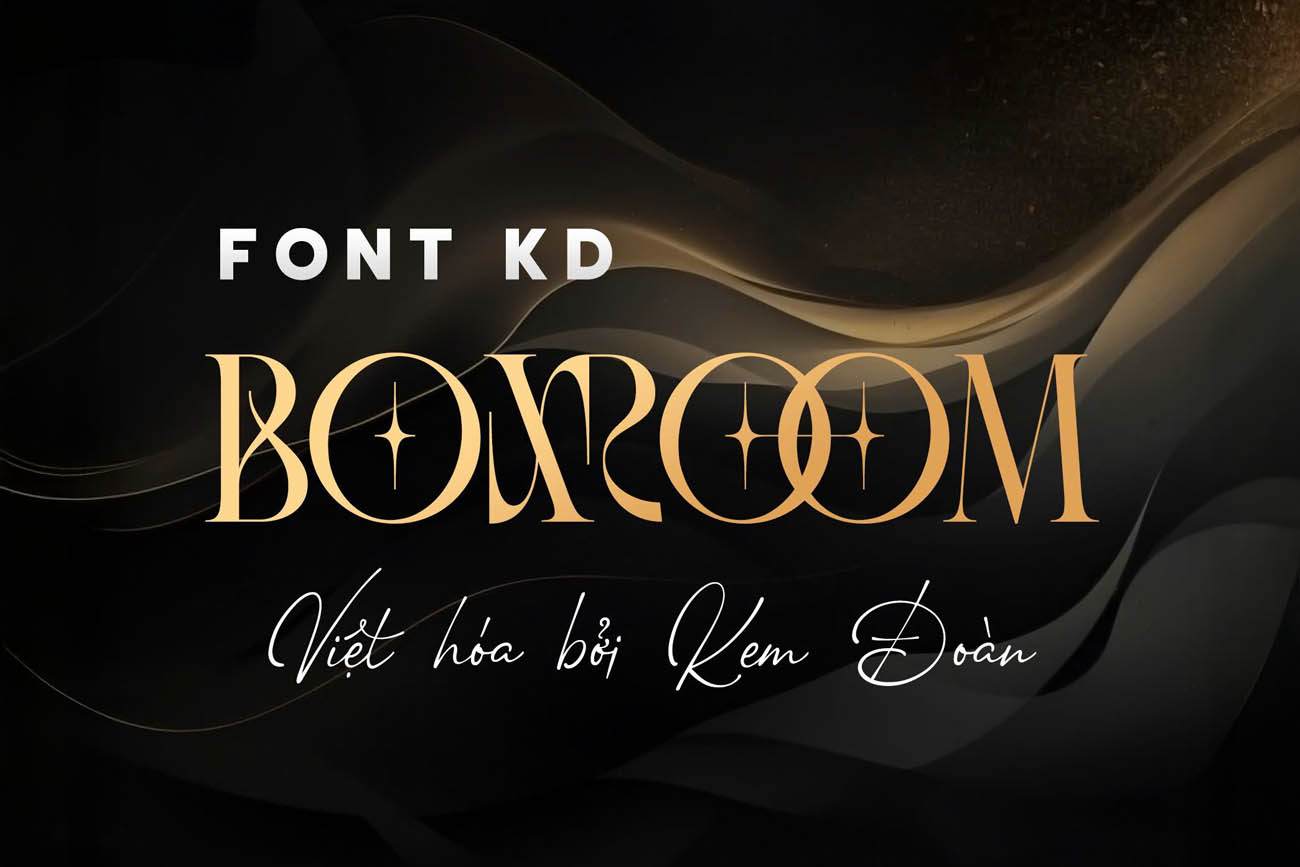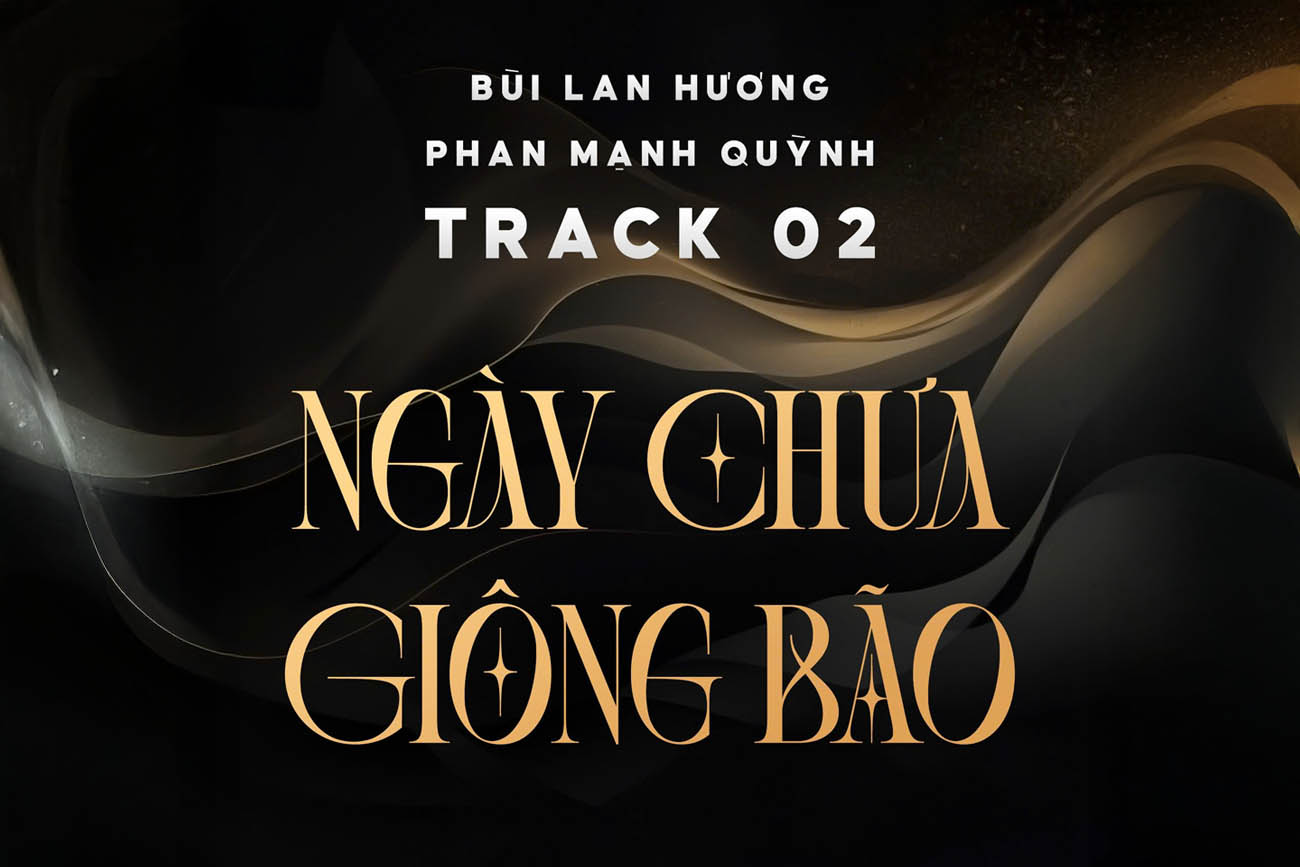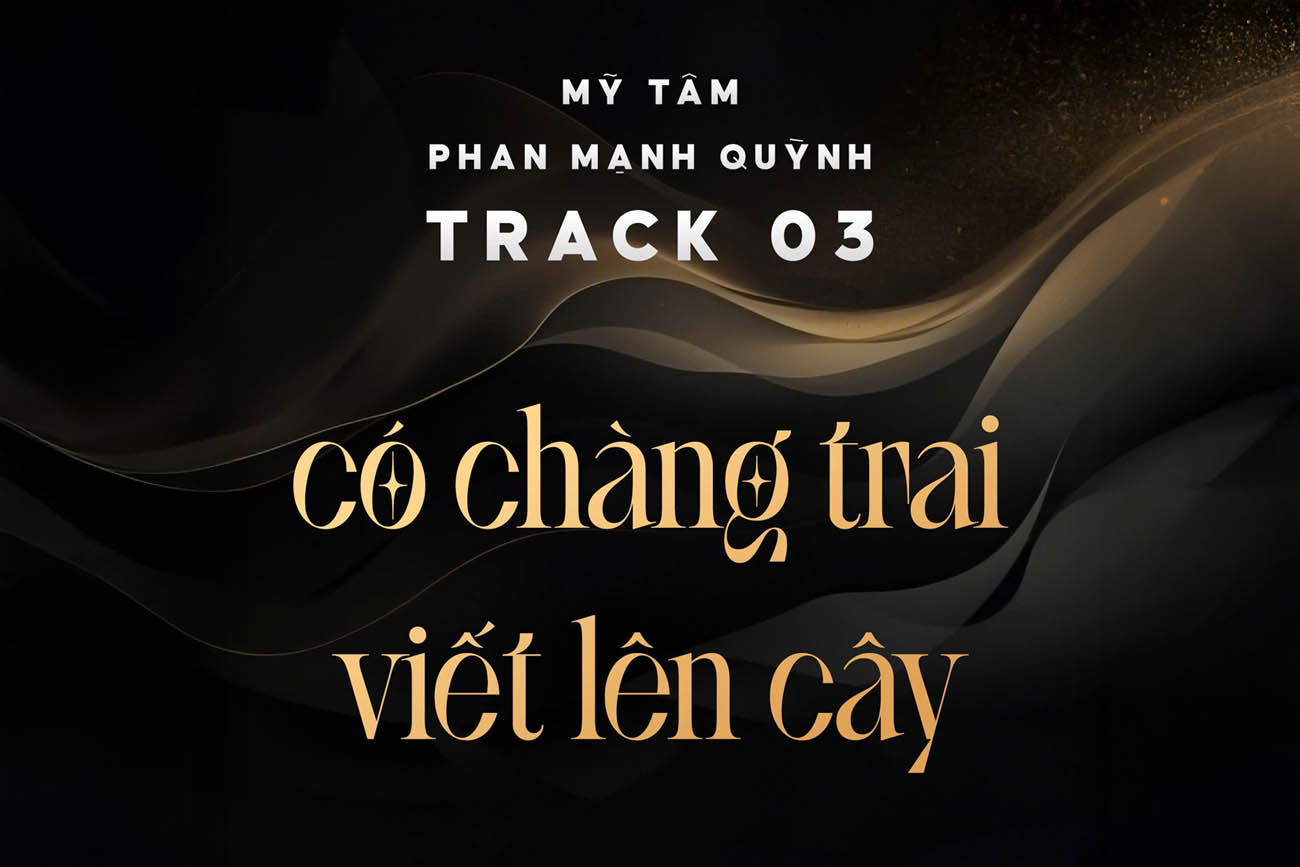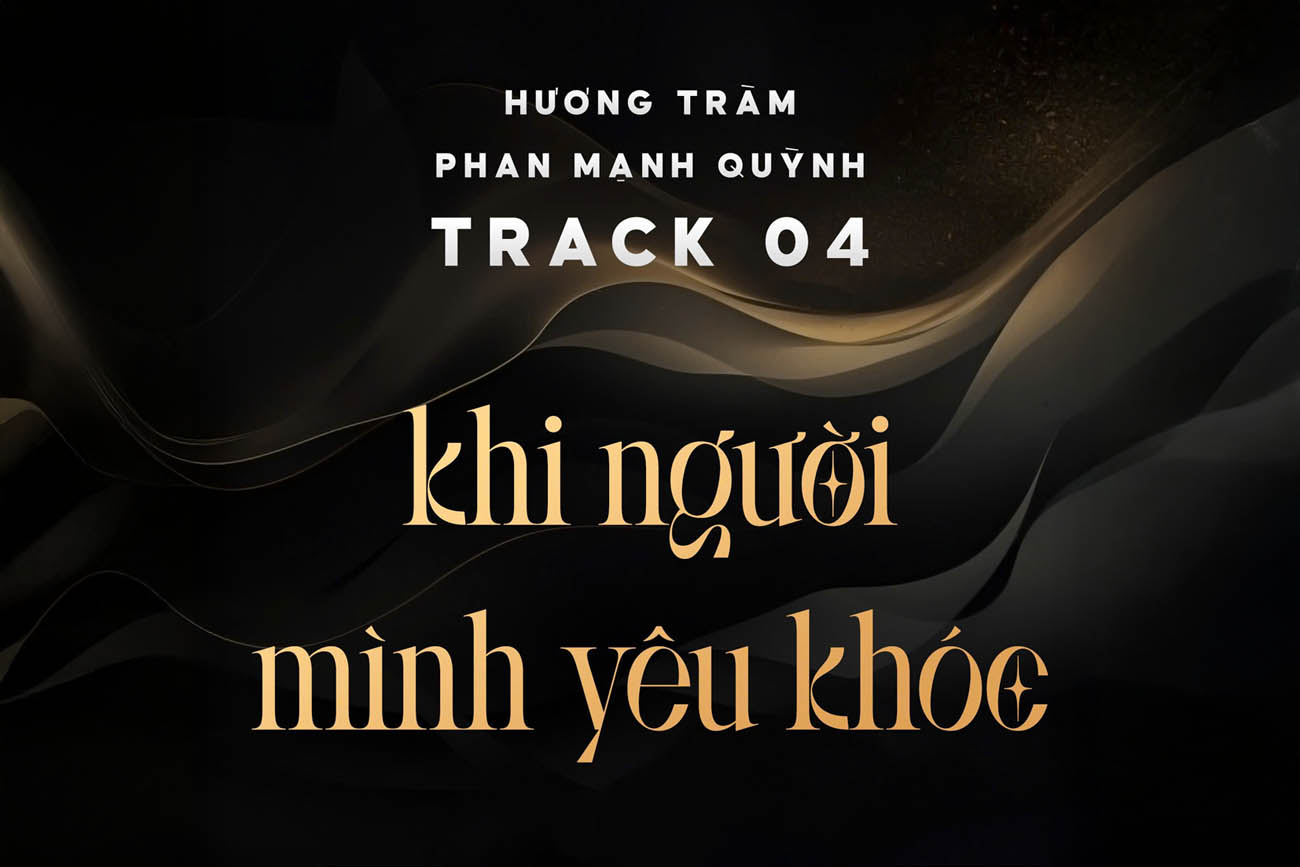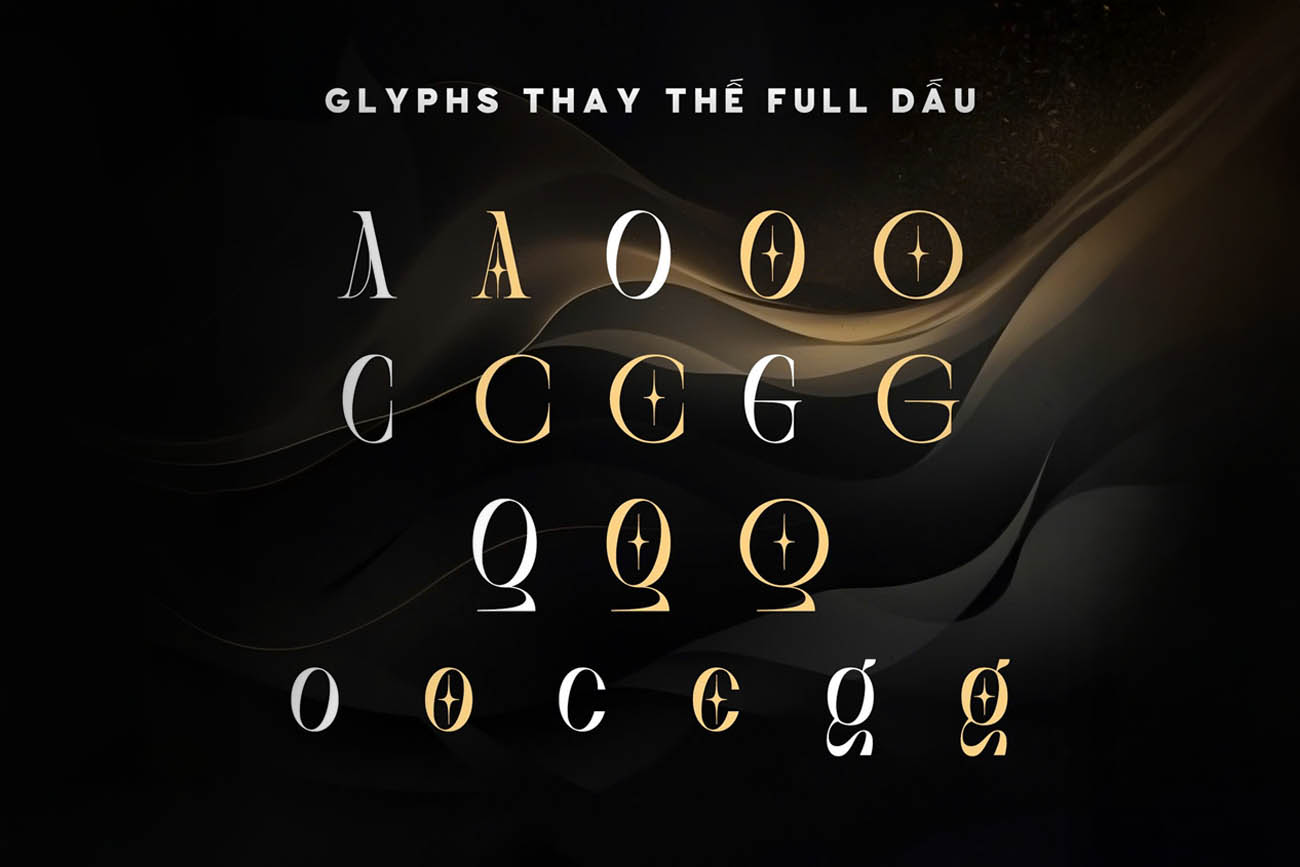
Font chữ KD Boxroom – Sang trọng, đẳng cấp và Việt hóa hoàn chỉnh
Trong thế giới thiết kế hiện đại, việc lựa chọn một bộ font chữ phù hợp không chỉ mang lại tính thẩm mỹ mà còn góp phần khẳng định giá trị thương hiệu. Font chữ KD Boxroom là một trong những lựa chọn nổi bật, đặc biệt dành cho những ai tìm kiếm sự sang trọng và tinh tế trong từng chi tiết.
Được thiết kế bởi Silver Stag – một nhà thiết kế typography nổi tiếng, Boxroom gây ấn tượng mạnh nhờ các đường nét thanh mảnh kết hợp cùng chi tiết trang trí ở giữa thân chữ, tạo hiệu ứng lấp lánh như ánh sáng. Sự độc đáo này khiến font vừa mang tính hiện đại, vừa gợi cảm giác cổ điển, phù hợp cho các dự án cao cấp.
Phiên bản font chữ Việt hóa do Kèm Đoàn thực hiện đã tối ưu hóa hoàn toàn cho tiếng Việt, bao gồm đầy đủ dấu và ký tự đặc trưng. Điều này giúp các nhà thiết kế có thể sử dụng linh hoạt trong nhiều ngữ cảnh khác nhau mà không lo thiếu ký tự.
Điểm nổi bật nhất của KD Boxroom nằm ở khả năng truyền tải sự xa hoa và tinh tế, biến mỗi con chữ thành một yếu tố nghệ thuật. Đây chính là lý do bộ font thường được gắn với các dự án mang tính luxury như logo thương hiệu thời trang, thiết kế bao bì mỹ phẩm, bìa tạp chí, thiệp mời cao cấp hay các ấn phẩm quảng bá sản phẩm sang trọng.
Ngoài ra, sự kết hợp giữa phông chữ serif cổ điển và những chi tiết hiện đại đã giúp KD Boxroom trở thành một lựa chọn đa năng. Font có thể ứng dụng tốt trong cả tiêu đề, typography nghệ thuật lẫn branding. Đặc biệt, khi phối hợp cùng màu sắc ánh kim hoặc hiệu ứng ánh sáng, bộ font càng toát lên vẻ đẹp quyền quý, đẳng cấp và khó nhầm lẫn.
Với thiết kế tinh xảo, bản Việt hóa hoàn thiện và khả năng ứng dụng rộng rãi, KD Boxroom không chỉ đơn thuần là một font chữ sang trọng, mà còn là công cụ giúp nhà thiết kế nâng tầm đẳng cấp cho mọi dự án sáng tạo